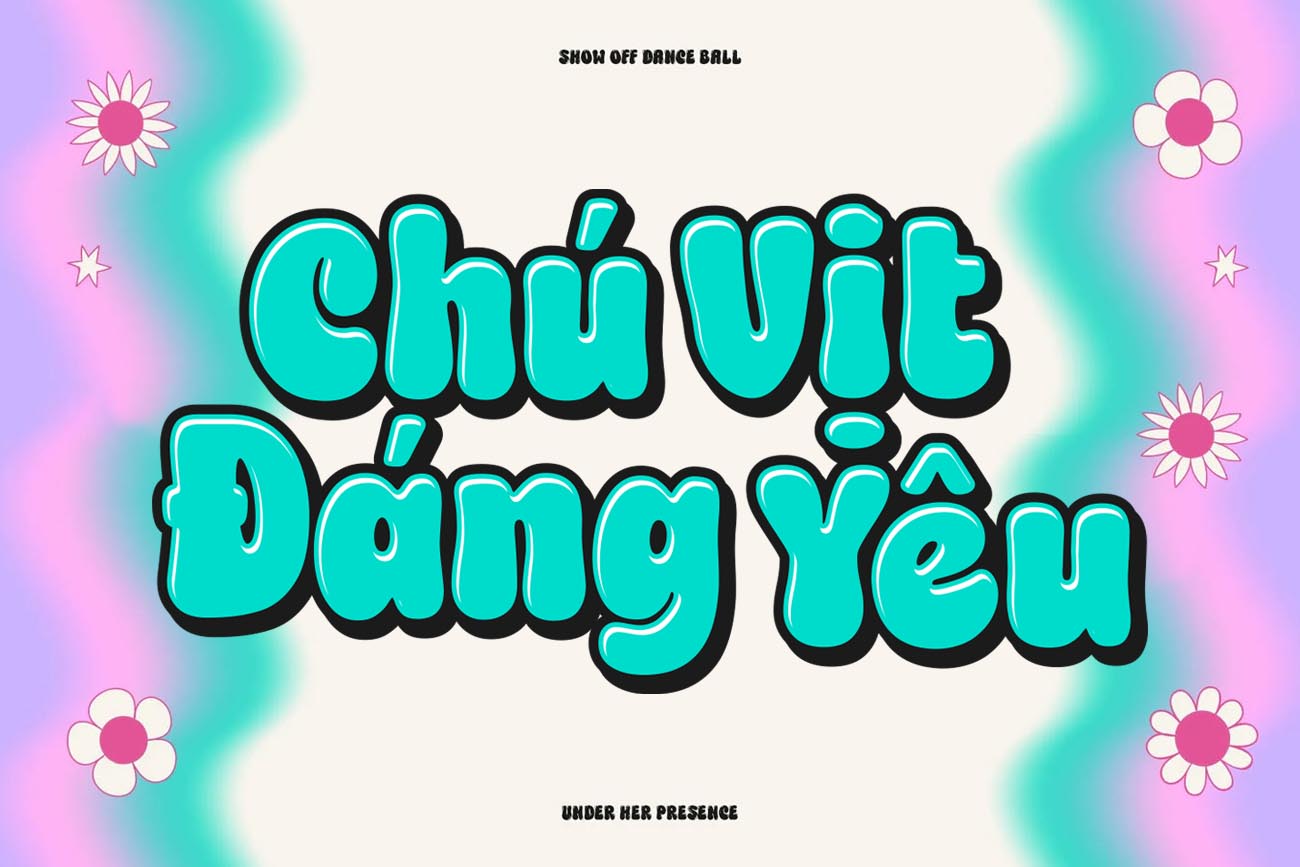
Font chữ hoạt hình TH Choret Fudyng Việt Hóa
Bạn đang tìm một font chữ béo tròn, hoạt hình siêu đáng yêu để thiết kế cho trẻ em, sản phẩm vui nhộn hay thương hiệu sáng tạo? Hãy khám phá Choret Fudyng Việt hóa – bộ font chữ bong bóng đầy màu sắc, năng lượng và độc đáo, nay đã hỗ trợ đầy đủ tiếng Việt.
Giới thiệu font Choret Fudyng Việt hóa
Choret Fudyng là một font display kiểu bubble được thiết kế bởi Alit Design Studio. Với phong cách tròn trịa, căng phồng như bong bóng xà phòng, font mang lại cảm giác vui nhộn, đáng yêu và cực kỳ bắt mắt. Phiên bản Việt hóa bởi SVN hoặc các nhà thiết kế trong nước đã bổ sung đầy đủ dấu tiếng Việt, đảm bảo dễ dùng và mượt mà trong mọi phần mềm thiết kế.
Vì sao Choret Fudyng là font chữ béo tròn lý tưởng?
Choret Fudyng Việt hóa là một trong những font chữ béo tròn lý tưởng cho thiết kế nhờ kiểu dáng tròn đầy, phồng to và ngộ nghĩnh. Font mang lại cảm giác thân thiện, vui nhộn, đặc biệt phù hợp với các dự án dành cho trẻ em, sản phẩm giải trí, đồ ăn nhanh hoặc game. Với nhiều biến thể như Regular, Bubble, Light và 3D, Choret Fudyng giúp tăng khả năng sáng tạo cho người thiết kế. Font còn hỗ trợ PUA Unicode, chứa ligatures thông minh và đã được Việt hóa chuẩn, không lỗi dấu – sẵn sàng ứng dụng trên mọi nền tảng thiết kế.
Ứng dụng của font chữ hoạt hình Choret Fudyng
• Poster hoạt hình, tiêu đề truyện tranh, kênh YouTube thiếu nhi
• Logo sản phẩm dành cho trẻ em, đồ chơi, bánh kẹo
• Thiết kế bao bì, nhãn dán, sticker cute
• Typography dùng trong mạng xã hội, video, banner quảng cáo
Choret Fudyng Việt hóa không chỉ là một font chữ béo tròn hoạt hình đơn thuần, mà còn là công cụ truyền tải cảm xúc vui nhộn, đáng yêu và thân thiện trong mọi thiết kế. Dù bạn đang làm poster cho thiếu nhi, thiết kế logo cho sản phẩm sáng tạo hay chỉ đơn giản là muốn tạo điểm nhấn dễ thương cho bài viết, Choret Fudyng đều đáp ứng hoàn hảo. Nếu bạn yêu thích sự tươi vui và năng động, đừng bỏ lỡ font chữ này – tải ngay về và bắt đầu thiết kế với thật nhiều cảm hứng!